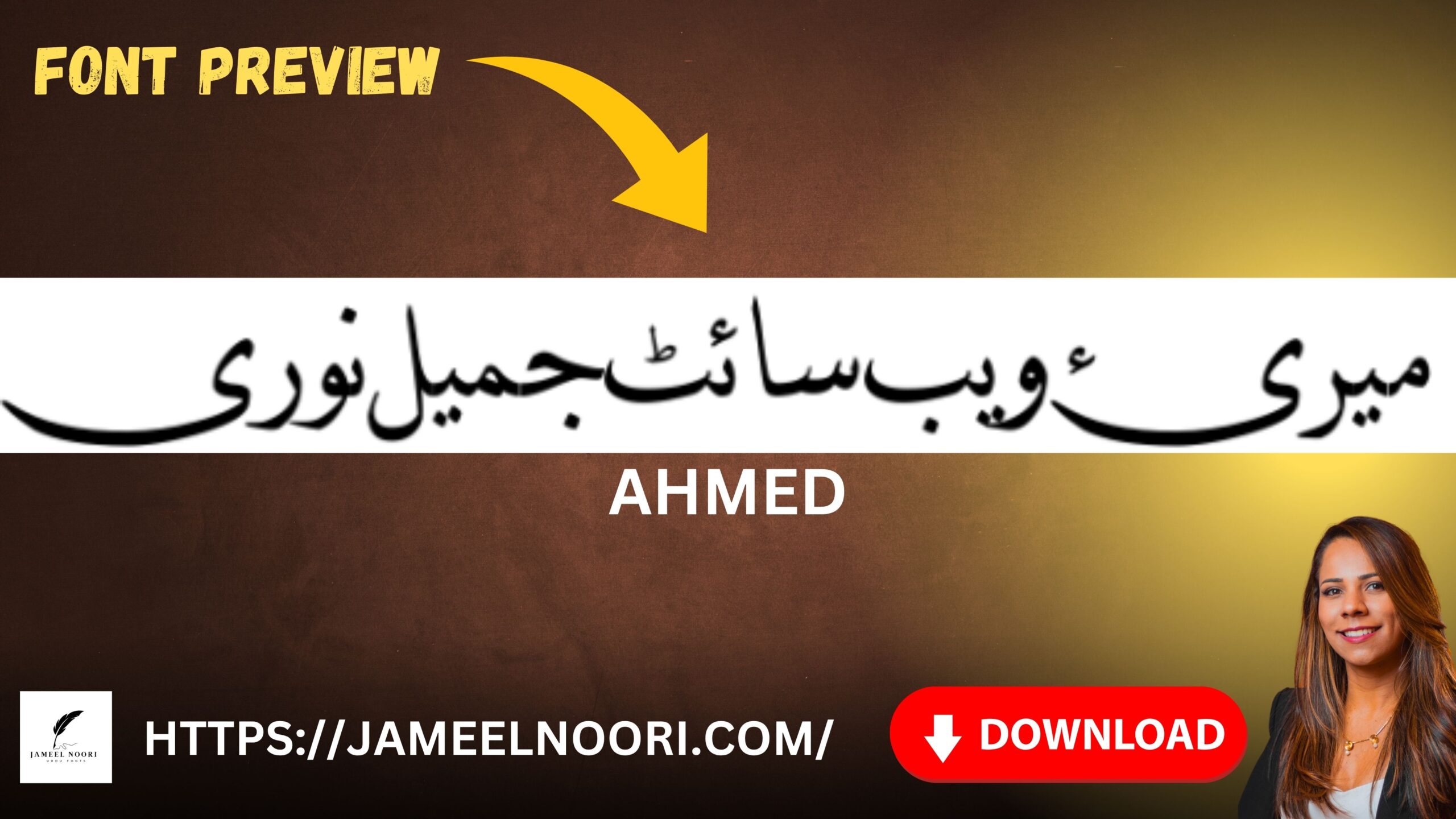
Introduction – Ahmed Urdu Font
Agar aap Urdu likhne walay designer ya content writer hain, to Ahmed Urdu Font aap ke liye ek zabardast choice ho sakta hai.. Yeh aik stylish aur user-friendly TrueType Urdu Font hai jo readability aur aesthetic design dono ko behtareen tareeqe se combine karta hai.. Is font ko ab tak 16,248 martaba download kiya gaya hai, aur users ne isay 3..82 out of 5 ka rating diya hai..
Why Ahmed Urdu Font is Special?
- ✅ Perfect for Urdu blogging, designing, or headlines
- ✅ Clear, neat aur stylish letter formation
Where You Can Use Ahmed Urdu Font (TTF)?
Ahmed Urdu Font ka use kai jagahon par kiya ja sakta hai:
- ✅ Graphic Designing Projects
- ✅ Urdu Poetry Writing in InPage or Photoshop
- ✅ Urdu Website Headlines
- ✅ Social Media Urdu Posters
- ✅ Urdu Blogging on Blogger/WordPress
Final Words
Ahmed Urdu Font aik stylish aur readable font hai jo Urdu content creation ko aur behtar banata hai.. Agar aap Urdu mein likhte hain ya design banate hain to yeh font lazmi download karein..